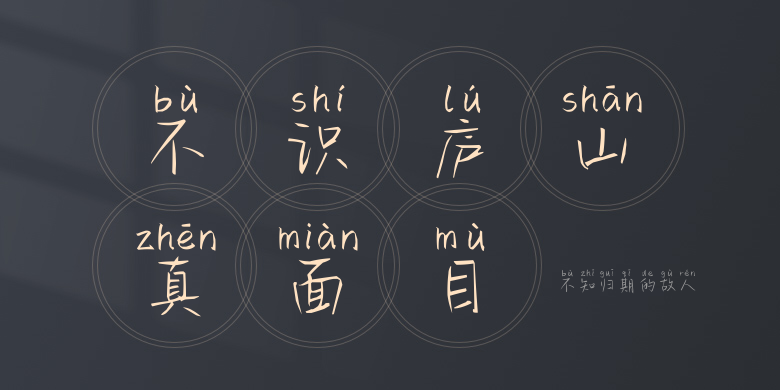
不知归期的故人
不知归期的故人,这款字体结构工整、笔画清晰,兼顾美观与易读性,适用于标题、正文、海报、包装、LOGO 等多种场景。字形优雅稳定,风格百搭耐看,适配日常排版与创意设计,让文字呈现更舒适、更具质感。不知归期的故人一笔一画,皆是细节,以均衡的比例、流畅的线条打造舒适视觉体验,字形端正大气,风格简约现代。无论是商业设计、品牌宣传还是日常排版,都能轻松驾驭,让文字更有格调与力量。不知归期的故人字体下载。